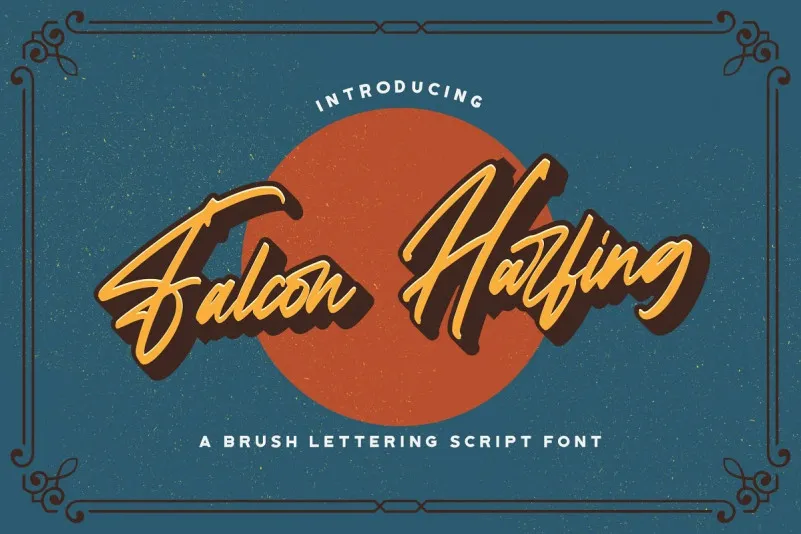
Falcon Harfing Font – Download Grátis
A Font ‘Falcon Harfing’ é uma seleção perfeita para aqueles que buscam uma nova maneira de expressar suas ideias criativas. Este script é intenso e funcional, com traços marcados e caracteres alegres. Seu estilo vintage arredondado oferece um toque único e inovador, ideal para marcas pessoais ou corporativos. A elegância e o charme desta font fazem-a uma escolha óbvia para qualquer projeto que busque trazer vida aos seus ideais criativos. Suas linhas curvas e suas formas arredondadas permitem uma expressão artística única, tornando a ‘Falcon Harfing’ uma opção versátil para design de marca, logos ou até mesmo textos em páginas web. Com sua simplicidade e complexidade em perfeita equilíbrio, este script é um complemento ideal para designers que procuram inovação na fontes. Seja você um artista digital ou designer gráfico, a ‘Falcon Harfing’ pode tornar seus projetos de design mais memoráveis.